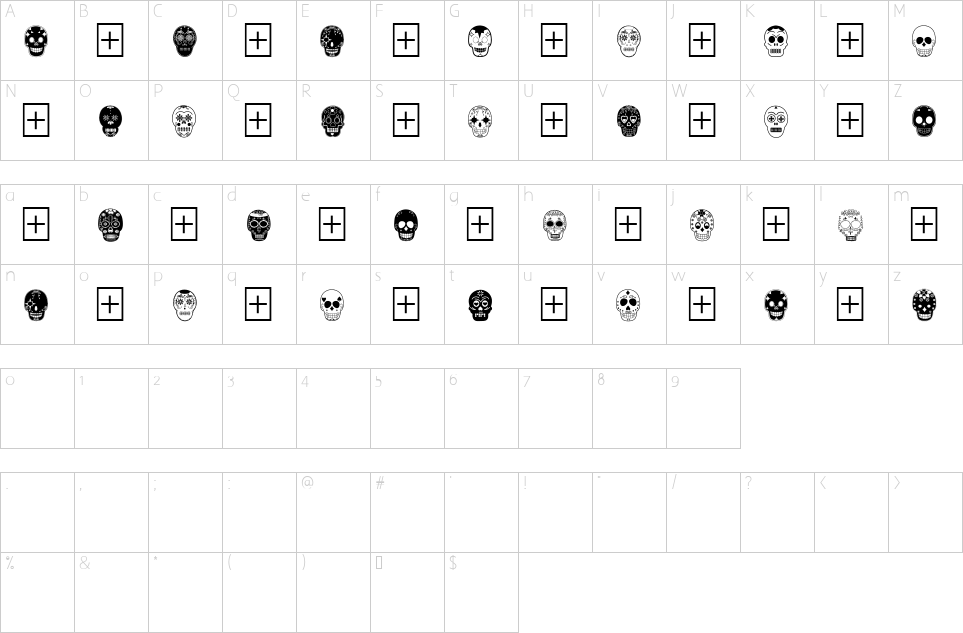
Esta página de download apresenta a “Dia de los Muertos Font”, uma elegante opção para aqueles que desejam adicionar um toque único e inspirador a seus projetos digitais. Desenvolvida por Intellecta Design, esta fonte é perfeita para quem busca expressar emoções profundas e memórias nostálgicas em sua obra. Com seu design cuidadosamente criado para representar o espírito do Dia de Muertos, essa fonte traz uma vibe mística que se encaixa perfeitamente com festivais e celebridades culturais. O fato de ter sido baixada 25,326 vezes é um indicativo de seu valor como recurso gráfico, tornando-a uma escolha ideal tanto para iniciantes quanto para profissionais que buscam trazer a paixão da cultura mexicana à sua arte digital. Sem dúvidas, esta fonte não apenas adere aos padrões do Dia de Muertos mas também oferece um toque inovador e pessoal às suas criações digitais.